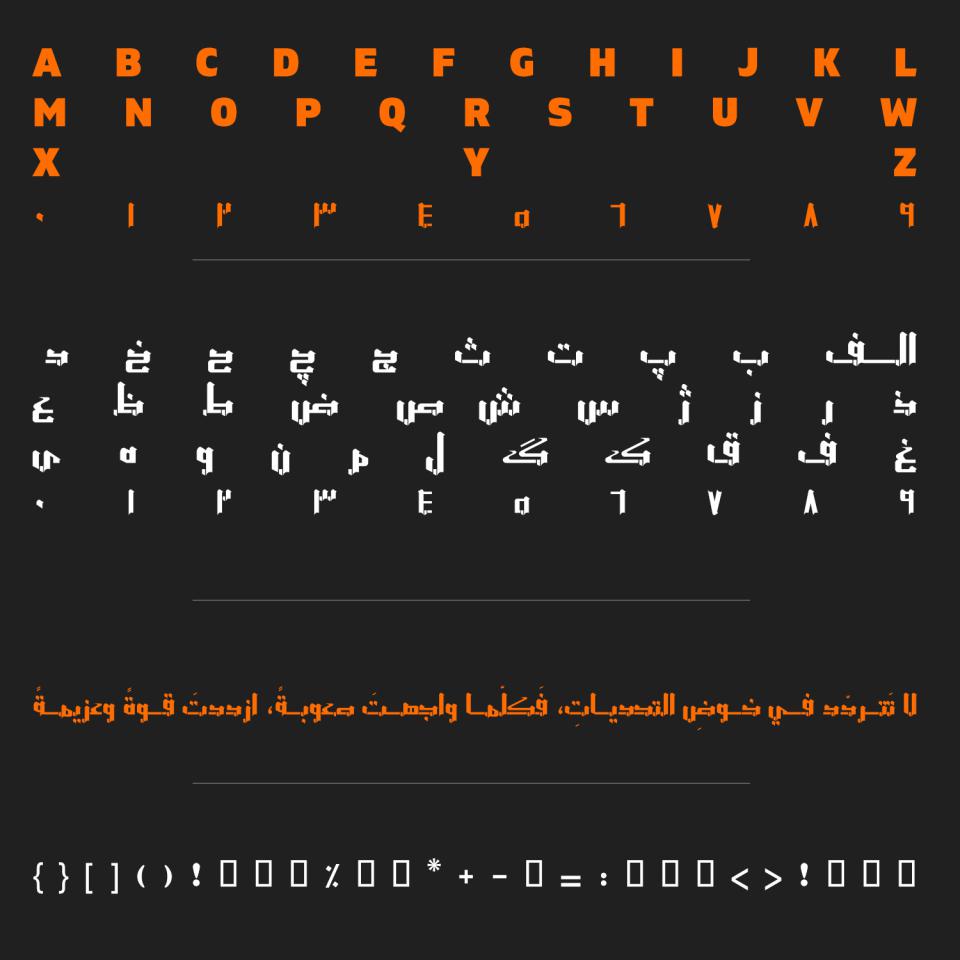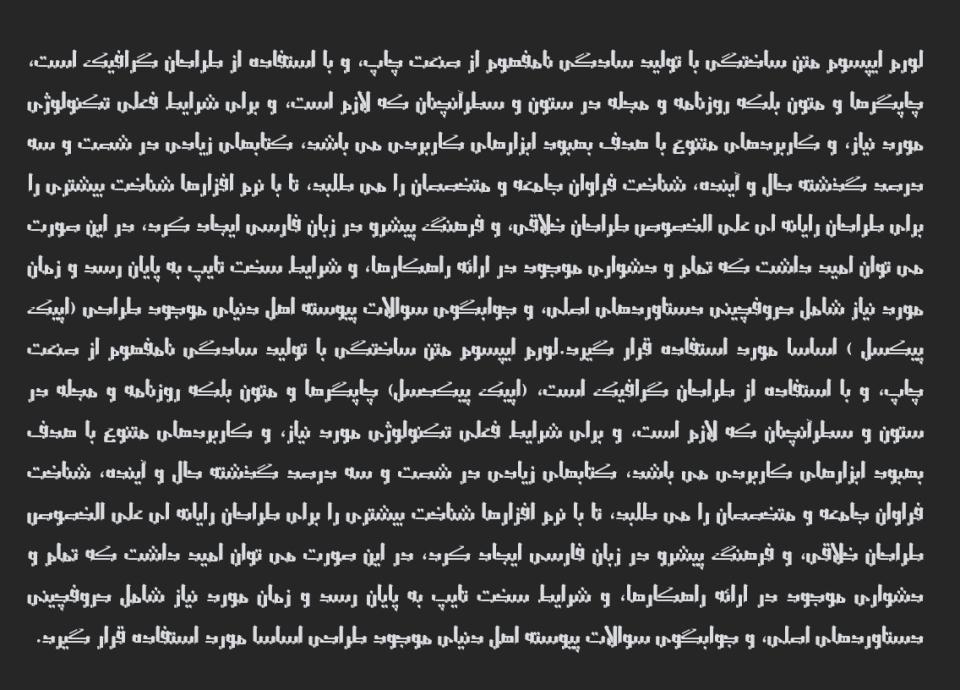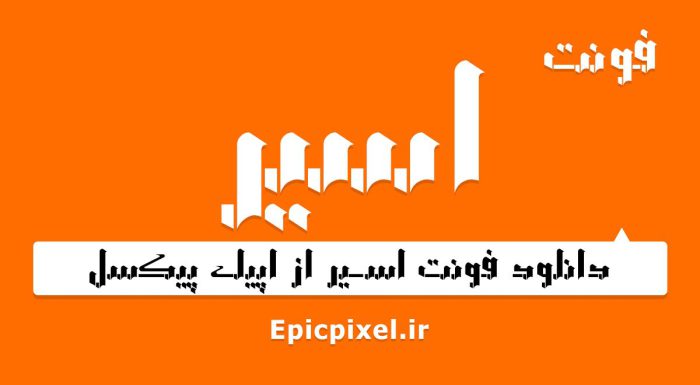
2 فونت اسیر فارسی
دانلود فونت اسیر فارسی به شما امکان می دهد تا به مجموعه ای غنی از حروف و نمادهای زیبا و خوانا با طرحی خاص و منحصربه فرد دسترسی داشته باشید که می تواند برای طراحی های گرافیکی، تایپوگرافی و ایجاد متون جذاب و چشم نواز در پروژه های شخصی یا حرفه ای تان، به صورت کاملا رایگان مورد استفاده قرار گیرد
فونت اسیر فارسی، با طراحی خاص و منحصربه فردش، حس نوستالژی و اصالت را به نوشته های شما می بخشد. این فونت با خطوط شکسته و زاویه دار، یادآور دست نوشته های قدیمی و خطاطی های سنتی ایرانی است و در عین حال، ظاهری مدرن و جذاب دارد. اگر به دنبال فونتی هستید که به طرح های گرافیکی، پوسترها، جلد کتاب ها و حتی نوشته های وبسایت شما، جلوه ای ویژه و متفاوت ببخشد، فونت اسیر انتخاب مناسبی است.
یکی از ویژگی های برجسته این فونت، خوانایی بالای آن در اندازه های مختلف است. چه در متن های کوتاه و چه در پاراگراف های طولانی، چشم به راحتی می تواند حروف را دنبال کند و خسته نشود. این ویژگی، فونت اسیر را برای استفاده در انواع پروژه ها، از طراحی لوگو گرفته تا نوشتن مقالات، مناسب می سازد. البته باید در نظر داشت که به دلیل فرم خاص حروف، شاید برای متن های بسیار طولانی و با اندازه قلم خیلی کوچک، کمی خسته کننده باشد.